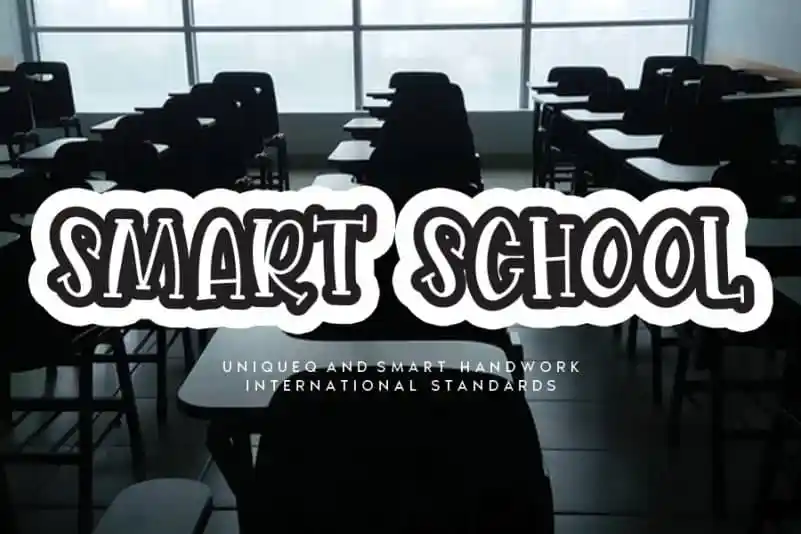
A Smart School Display Font é uma fonte de exibição encantadora e única que traz alegria para seus projetos. Seja você um designer criativo ou simplesmente alguém interessado na arquitetura visual, esta fonte adicionará um toque divertido e especial aos seus textos. Com um design fácil de ler, essa fonte irá destacar sua mensagem em qualquer projeto gráfico que você estiver trabalhando. Imagine a maneira como o seu texto ganha vida com esse detalhe único e divertido; ela é certamente uma escolha perfeita para criar uma experiência visual única em seus projetos. Seja para cartazes, materiais educacionais ou mesmo em um logotipo de marca inovador, a Smart School Display Font vai garantir que seu design seja notado no meio do desfile de criatividade. Experimente e veja como ela pode transformar sua arte digital!